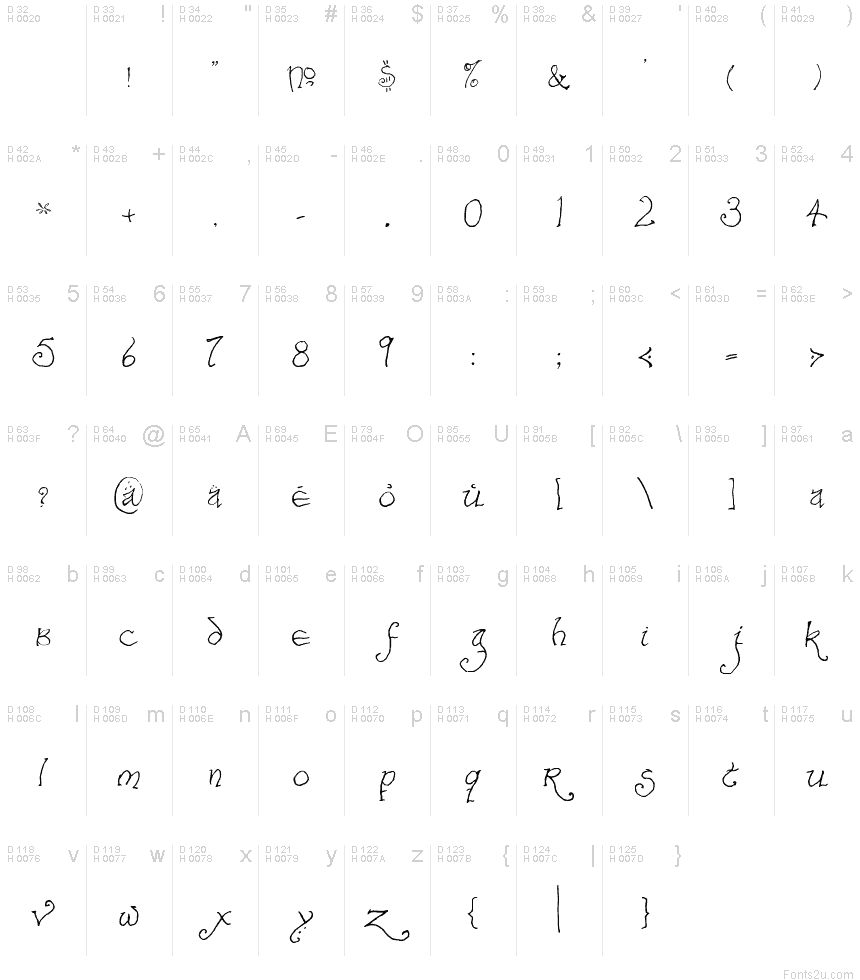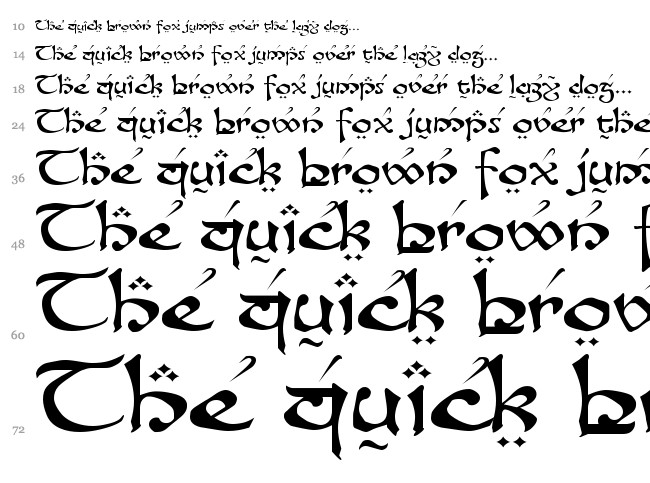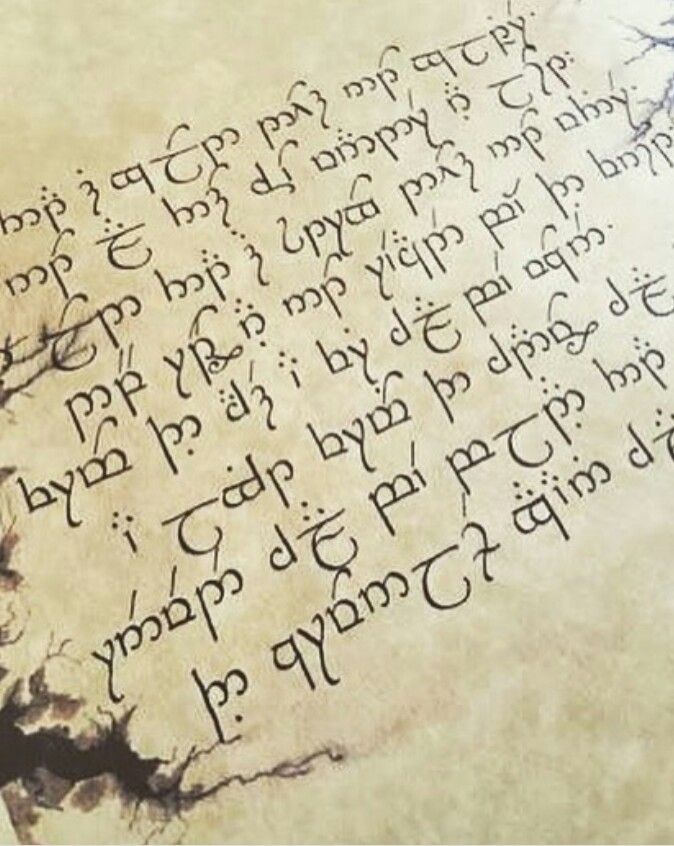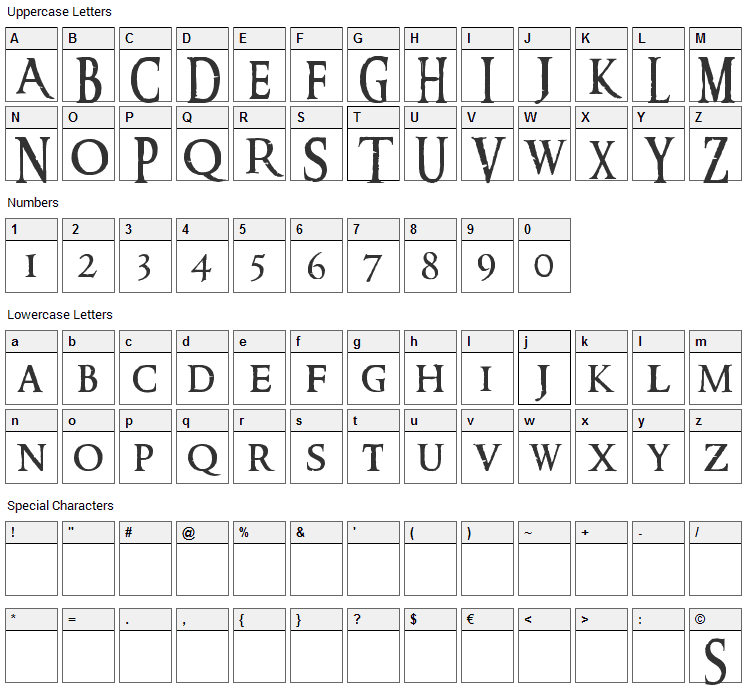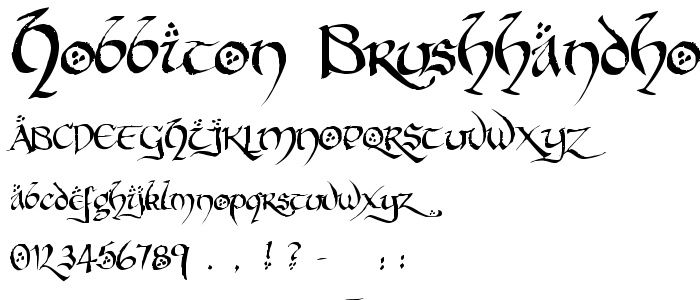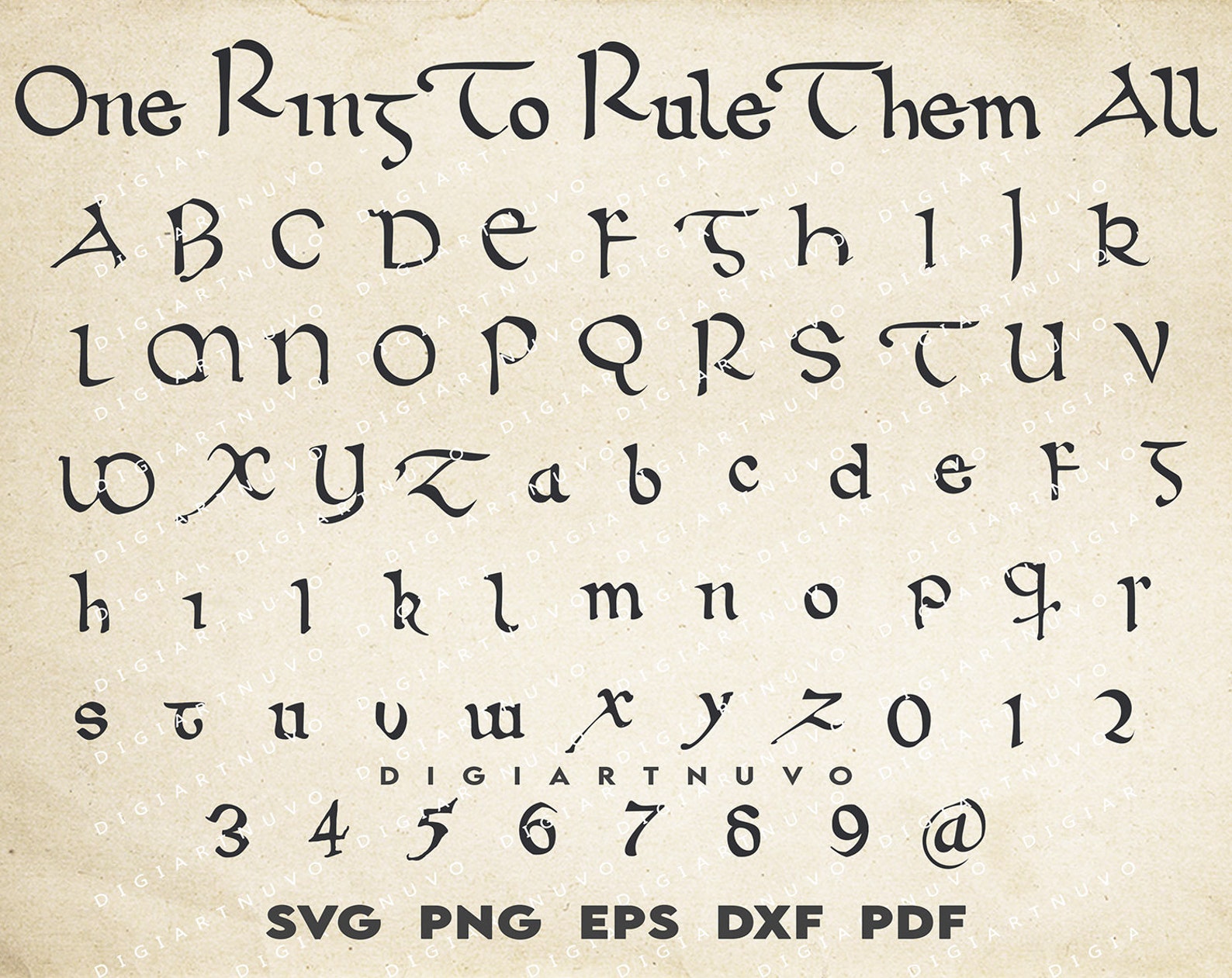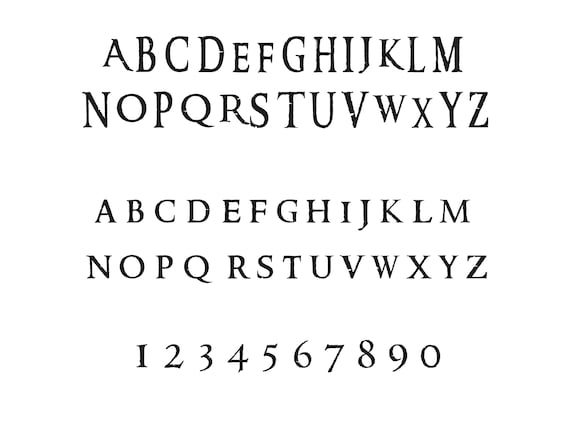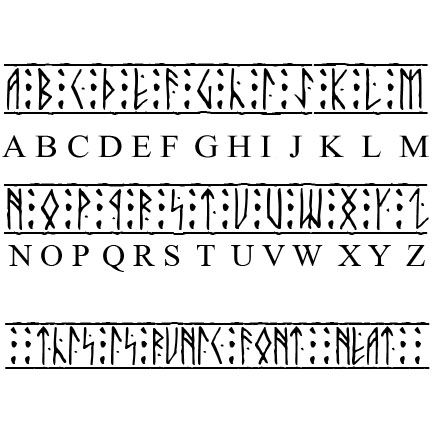
Чем бы была трилогия Властелин Колец без его знакового логотипа? Желтые, будто вытесанные из камня буквы – практически идеальный логотип для эпичного кино. Но это не единственный из характерных шрифтов, использованных в трилогии Властелин Колец и ее рекламных материалах. Большинство из этих шрифтов перекочевало и в Хоббита – но что это за шрифты, и где их можно взять?
Шрифты имеют значение. Иногда правильный шрифт – единственное, что отличает многообещающий, но очевидный фан-арт от профессионально выглядящего дизайна. Будучи сам в некотором роде шрифтовиком, должен признаться: шрифты – в какой-то мере мой конек. Поэтому я и решил написать это руководство: представить самые основные из гарнитур, что использовались в обоих фильмах Питера Джексона о Средиземье: Властелин Колец и Хоббит.
Чем это руководство не является – так это руководством по шрифтам к языкам Толкина (эльфийским, гномьим и прочим) – так как это отдельная, крайне обширная тема. В данной статье основной упор делается на шрифтах, что использовались в фильмах и в их рекламных материалах.
Я разбил шрифты на категории: те, что используются в самих кинофильмах, и те, что используются для маркетинга. Приставка «Фильм» обозначает шрифт, использованный в фильме, а «Маркетинг» — шрифт, использовавшийся для плакатов, роликов и прочего мерчандайзинга. Есть еще одна особая категория – для шрифтов, использованных сугубо для DVD/BluRay. Шрифты отсортированы в порядке значимости.
О кириллице: там, где я знаю, что для того или иного шрифта существует кириллица, я это особо указываю.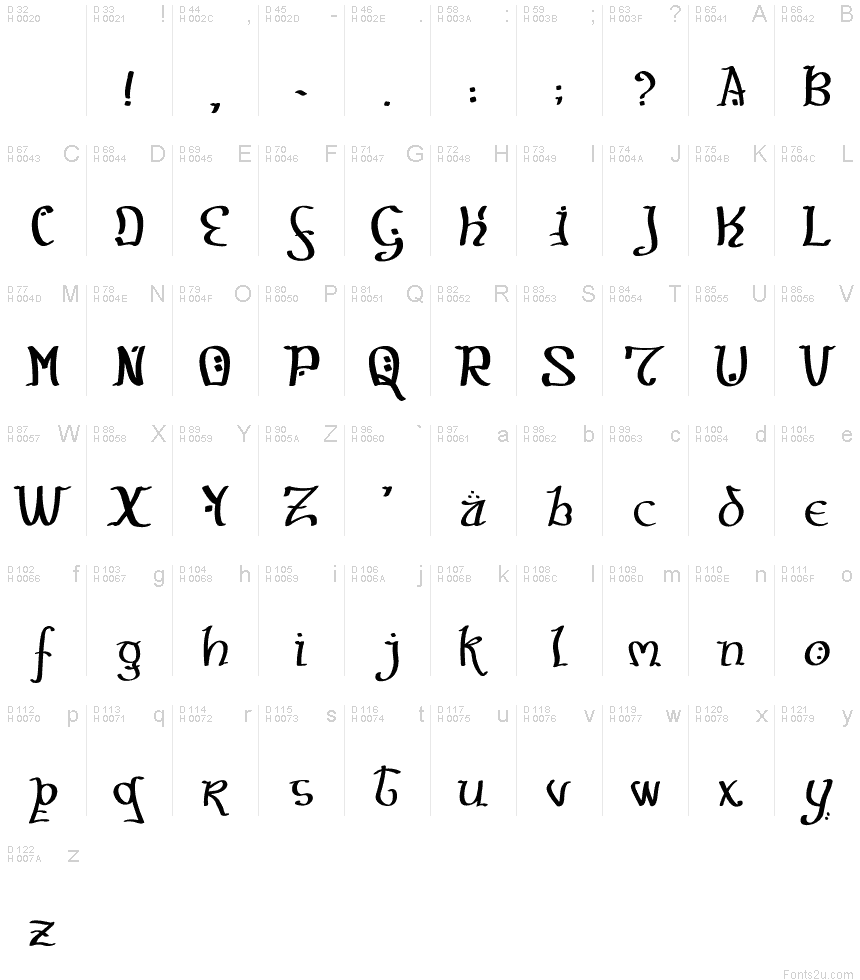
К несчастью, для названия фильма, показанного в фильмах Властелин Колец и Хоббит, шрифта не существует. Логотипы, как и их международные варианты, были созданы Аланом Ли и нарисованы от руки. Правда, если собрать все международные варианты заставки, теоретически можно бы было сделать из этого целый шрифт. Но пока этого еще никто не сделал.
Фильм: Названия частейЛоготипы к каждой части фильма (The Fellowship of the Ring итд.) нарисовал каллиграф Даниэль Рив (Daniel Reeve). У каждой части – свой дизайн (исключение – Возвращение Короля и Нежданное Путешествие, где используется один и тот же шрифт). Кстати, логотип Пустоши Смауга отличается по стилю от предыдущих частей – он тоже нарисован вручную Даниэлем Ривом, который, кстати говоря, взял за основу мой шрифт Ringbearer.
На текущий момент шрифтов по логотипам серий не существует.
Однако, следует учесть, что Даниэль создал не только все логотипы, но и все их международные варианты (по крайней мере, для ВК). То есть, строго говоря, если добыть все международные варианты в хорошем качестве, можно бы было экстраполировать достаточно букв, чтобы создать из них целый шрифт.
Маркетинг: Название фильма
Один из самых знаковых шрифтов в Властелине Колец и Хоббите – логотип названия, который используется на плакатах, обложках, в мерчандайзинге, итд. Этот шрифт называется Sauron и был создан американской компанией The Ant Farm специально для кинотрилогии ВК. Во времена ВК он, кроме как в логотипе, особенно не светился (хотя он также использовался в бонусах расширенной версии ВК). Зато для Хоббита его начали серьезно использовать в целях мерчандайзинга. Тем не менее, Sauron – лишь шрифт-заготовка, и для создания логотипов внешний вид разных букв подвергался серьезным модификациям.
К примеру, обе буквы «B» в логотипе «Hobbit» очень отличаются друг от друга. Ну и еще: в этом шрифте и верхний, и нижний регистр – практически идентичные. Sauronне предназначен для публичного использования и доступен лишь партнерам New Line/Warner.
Примечание: для русского плаката к первой серии ВК использовался другой шрифт. Он также используется в логотипах лицензионных DVD/BluRay Властелина Колец.
Существует альтернатива к Sauron, которую я создал в 2002 году: RingbearerMedium. Для ее создания я исследовал разные международные логотипы фильма Властелин Колец, чтобы определить внешний вид разных букв. Некоторые из них довольно существенно отличаются и от Sauron, и от официальных логотипов. Этот шрифт – бесплатный для некоммерческих целей; его можно скачать здесь.
Кириллица: в моем шрифте ее нет; хотя я видел более-менее кривые русификации.
Маркетинг: Названия частей
Второй по важности шрифт для ВК – Albertus, который используется для названий отдельных серий (наподобие The Fellowship of the Ring), а также для прочих надписей на плакатах Хоббита.
Этот шрифт был создан дизайнером Бертольдом Вольпе и назван в честь немецкого философа Альберта Великого (Albertus Magnus). Существуют многочисленные версии этого шрифта, в том числе версия Linotype (здесь) и Monotype (здесь). Еще существует альтернатива под названием FlareSerif 821 BTRoman.
Кириллица есть в варианте Albertus компании ElseWare.
Кельт
Шрифт похож на тот, что используется в фильме.
Bay Animation Inc., 1994
Лунные руны
неизвестный автор
Партийный бизнес
Шрифт с вывески у двери Бильбо
Нэнси Лоренц, 2002
Англосаксонские руны — 3 шрифта
Дэниел Стивен Смит, 1998
Гномьи руны — 3 шрифта
Дэниел Стивен Смит, 1998
Германские руны — 3 шрифта
Дэниел Стивен Смит, 1998
Рунический — 3 шрифта
Западный шрифт в руническом стиле.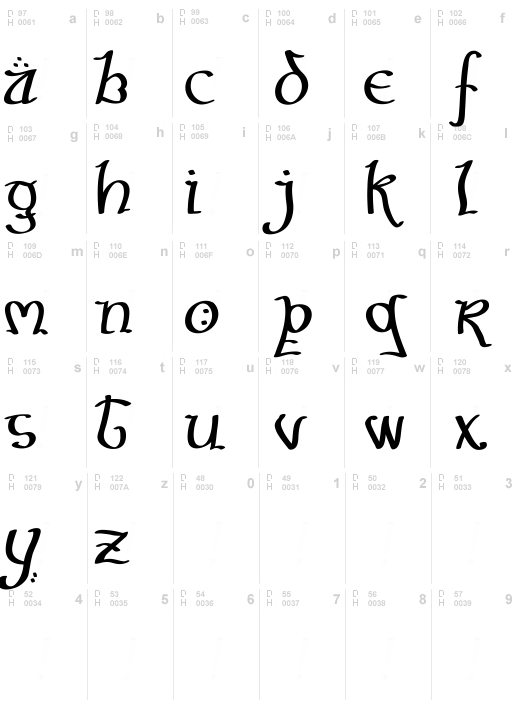